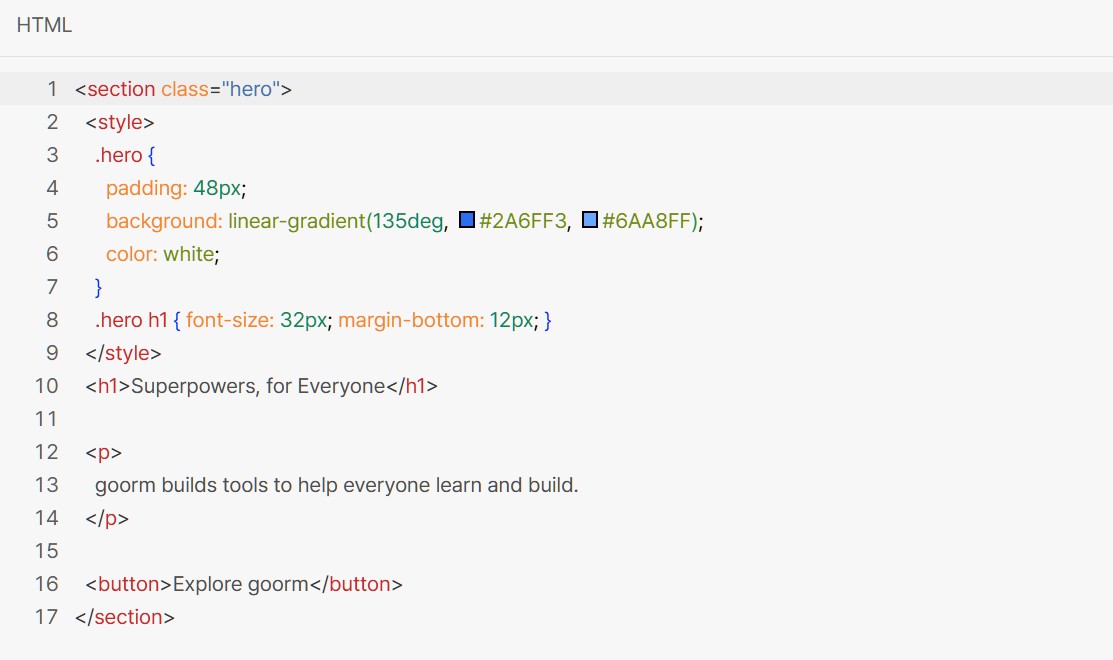
구름산스 무료폰트
구름산스 — 구름에서 배포하는 무료 폰트입니다. 긴 시간 코드를 쓰거나 화면을 보는 사람의 눈 피로를 줄이려 다듬은 부드러운 산스 서체
클라우드 개발 환경을 만드는 구름이 자사 브랜드를 담아 개발한 전용 서체입니다. 눈에 띄는 점은 만들 때 상정한 사용자입니다. 제작사는 긴 시간 코드를 작성하거나 화면을 바라보는 환경을 염두에 두고 눈의 피로를 줄이는 데 주의를 기울였다고 밝히고 있습니다.
제작사가 밝힌 조형의 핵심은 안정적인 골격과 일정한 자폭입니다. 파일에서 재어 보면 받침 유무에 따른 높이 차가 거의 없는 네모틀이고 낱자는 정사각형에 가까우며, 가로세로 획 굵기 차이가 14% 정도로 고른 민부리입니다. 현대 한글 11,172자를 모두 담아 조합에 따라 글자가 빠지는 일이 없습니다.
패밀리가 두 갈래인 점이 이 서체의 특징입니다. 문서와 디자인에 쓰는 구름 산스와, 코드 에디터를 위한 고정폭의 구름 산스 코드가 따로 있습니다. 코드 쪽은 한글과 영문의 자폭을 코드 안에서 일관되게 맞춰 시각적으로 구분되도록 했습니다. 굵기는 Regular와 Medium, Bold 세 가지라 본문과 제목을 나누기에는 넉넉하지만 아주 굵거나 아주 가는 표현이 필요한 디스플레이 조판에는 여유가 적습니다.